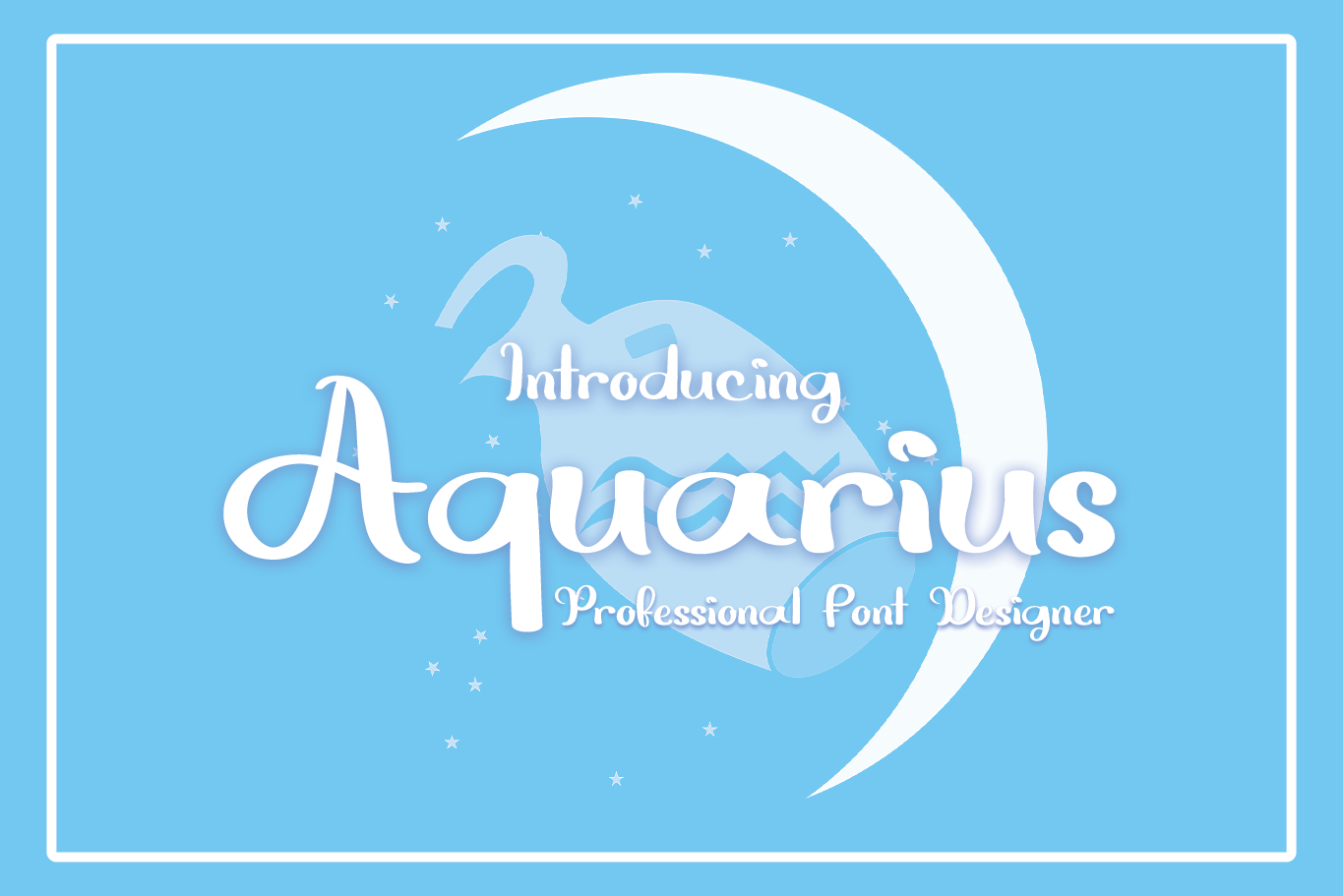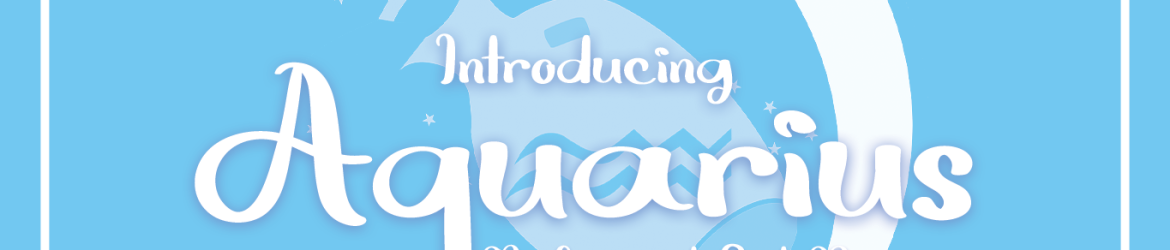
A fonte ‘Aquarius’ é uma elegante caligrafia bold que oferece um toque sofisticado aos seus designs. Ela foi especialmente criada para quem procura uma aparência fresca e agradável, sem perder o charme do estilo handwritten. Este design de letras delicadas vai tornar qualquer projeto mais arrumado e atraente, garantindo um ar contemporâneo em suas criações. Seja você designer gráfico ou web, ‘Aquarius’ é uma escolha perfeita para quem quer dar um toque especial às suas obras, sem abrir mão da elegância e do requinte que o estilo handwritten oferece.